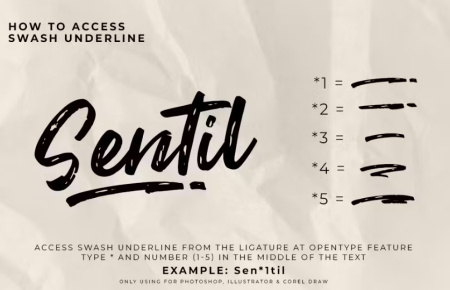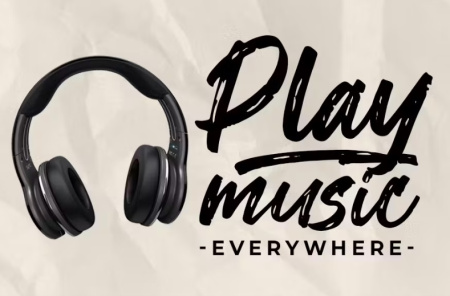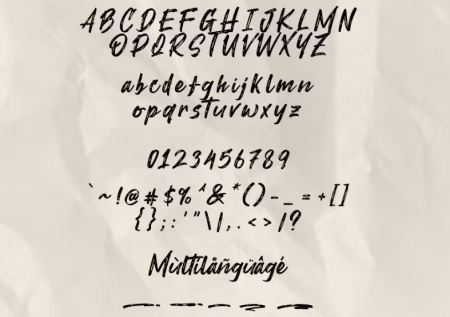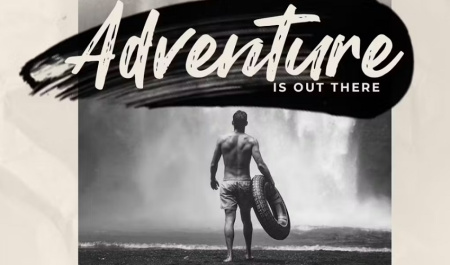
فونت انگلیسی رایگان Vontjack
فونت انگلیسی رایگان Vontjack که به صورت کاملا رایگان در سایت gfx در اختیار شما کاربران عزیز قرار داده شده است. یک فونت جدید، مجموعه کاراکترهای ظریف و مدرن است. فونت انگلیسی Vontjack با قابلیت پشتیبانی چند زبانه می باشد.